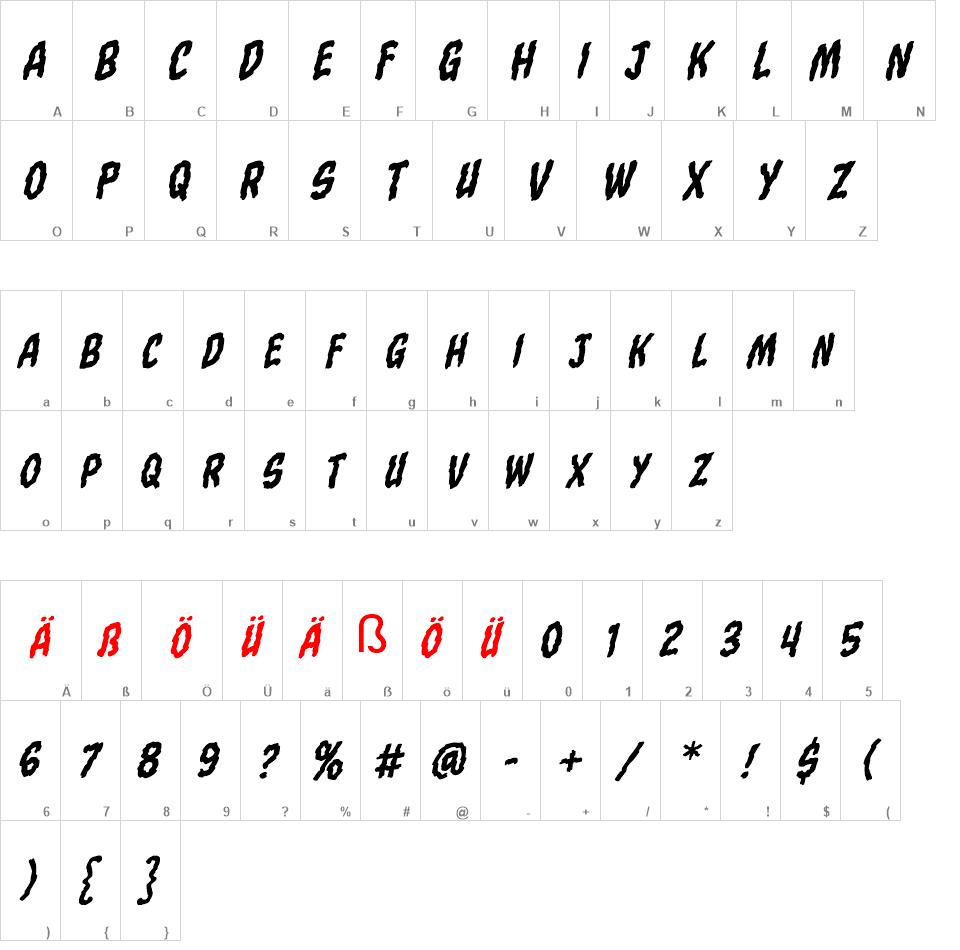
Torn Asunder BB Font Family
Inspiriert von klassischen Sound-Effekte-Schriftzügen ist dieses distressed Set perfekt für gammabestrahlte und steinhäutige Muskelköpfe geeignet. Beinhaltet Regular und Italic und hat einige grundlegende internationale Charaktere!